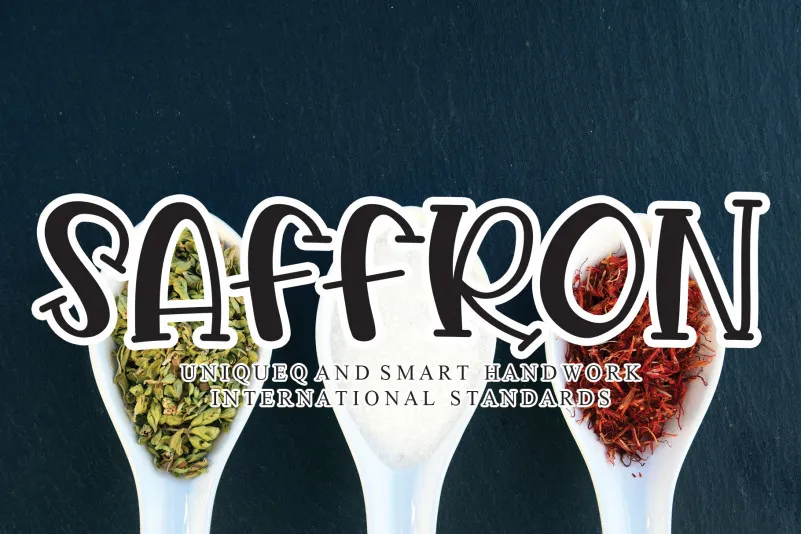
Saffron Display Font é uma elegante e desafiadora família de fontes para uso em exibição. Com seu design retrô minimalista e cores alegres, essa fonte transformará seu próximo projeto em algo verdadeiramente especial. Perfeita para um toque único no entrelaçamento de textos ou para gráficos chamativos, Saffron Display Font eleva qualquer conceito de design ao nível do luxo. Ideal para designers que buscam uma fonte não só versátil e atraente, mas também moderna e divertida, essa família de fontes é certamente um investimento valioso para seu arsenal. Seja você criando materiais de marketing ou projetos gráficos, o brilho deslumbrante da Saffron Display Font trará vida à sua arte com uma presença visual que deixará todos impressionados.